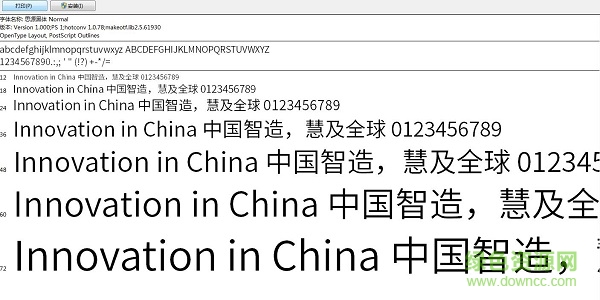
思源黑體normal字體
思源黑體normal字體是一款可以適應(yīng)屏幕用字需求的高品質(zhì)黑體字體,字面開闊,整體結(jié)構(gòu)協(xié)調(diào),識(shí)別度高,用在正文排版、網(wǎng)頁(yè)設(shè)計(jì)、平面設(shè)計(jì)等領(lǐng)域都能可以,感興趣的朋友快來(lái)下載吧!
字體特點(diǎn)
1.不但適用于印刷媒介,還可用于屏幕閱讀;
2.撇、捺、鉤筆畫的粗細(xì)變化不大;
3.美觀大方,應(yīng)用范圍廣等。
sourcehansanssc normal字體